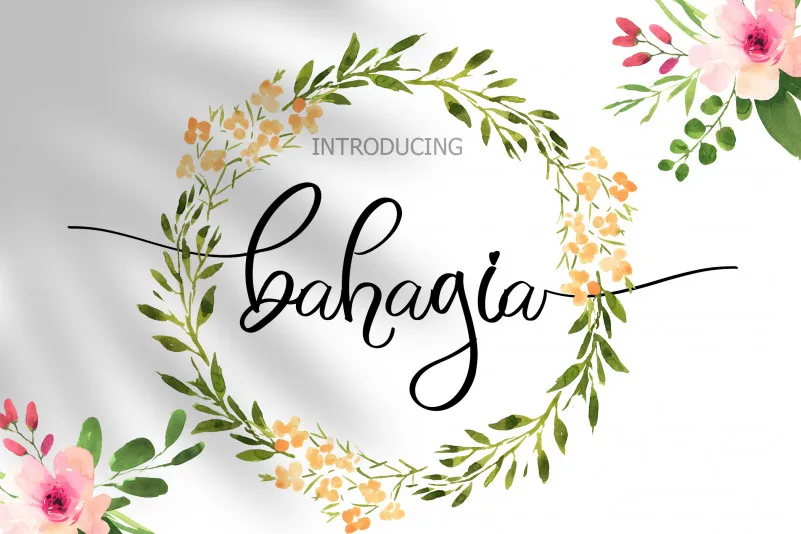
Bahagia Font – Fonte Grátis
Bahagia Font
A Bahagia Font é uma elegante tipografia de mão escrita leve com um toque único e impactante. Ela se destaca não apenas pela sua beleza visual, mas também pelo seu charme refinado que pode transformar qualquer projeto gráfico. Perfeita para adicionar um toque luxuoso a projetos de design pessoais ou profissionais, a Bahagia Font é uma escolha inteligente para aqueles que buscam dar um toque especial em seus trabalhos visuais. Com sua facilidade de usar e versatilidade, ela se adequa perfeitamente a diversos estilos e formatos, tornando-a uma opção indispensável no seu arsenal de fontes digitais. A Bahagia Font é o resultado de criatividade e precisão, oferecendo aos designers o poder para criar designs que não só são visuaismente atraentes, mas também carregam um significado profundo.